Вводите имя, выбираете стиль, скачиваете PNG. Вот и всё, уходит секунд десять.
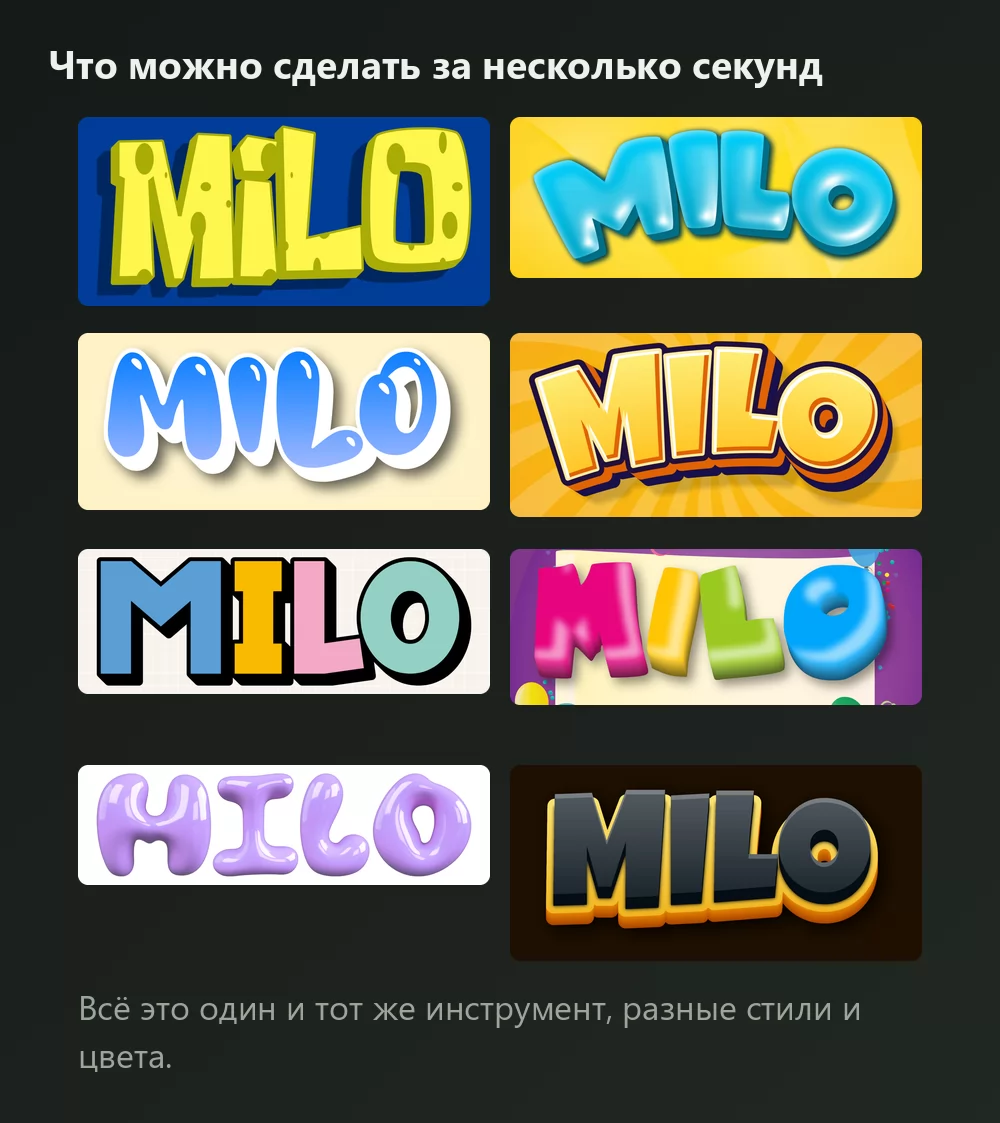
Всё это один и тот же генератор шрифта «Губка Боб», просто с разными стилями из списка. Ничего не устанавливается, аккаунт не нужен.
Как сделать текст в стиле «Губка Боб»
Шаг 1. Введите имя
Откройте генератор и замените образец текста на свой: имя, праздник, канал, заголовок. Буквы перерисовываются по мере ввода.
Шаг 2. Выберите стиль
Стиль сериала это жёлтая губчатая текстура с дырками и толстой тёмной обводкой. Именно его все и представляют, и он самый громкий из набора. Во вкладке «Стили» заливка, обводка и тень меняются по отдельности: форма остаётся, громкость убавляется.
Шаг 3. Выберите формат
Задайте формат до экспорта, и потом ничего не обрежется. 16:9 для превью видео, квадрат для аватара, широкая полоса для праздничной растяжки.
Шаг 4. Скачайте
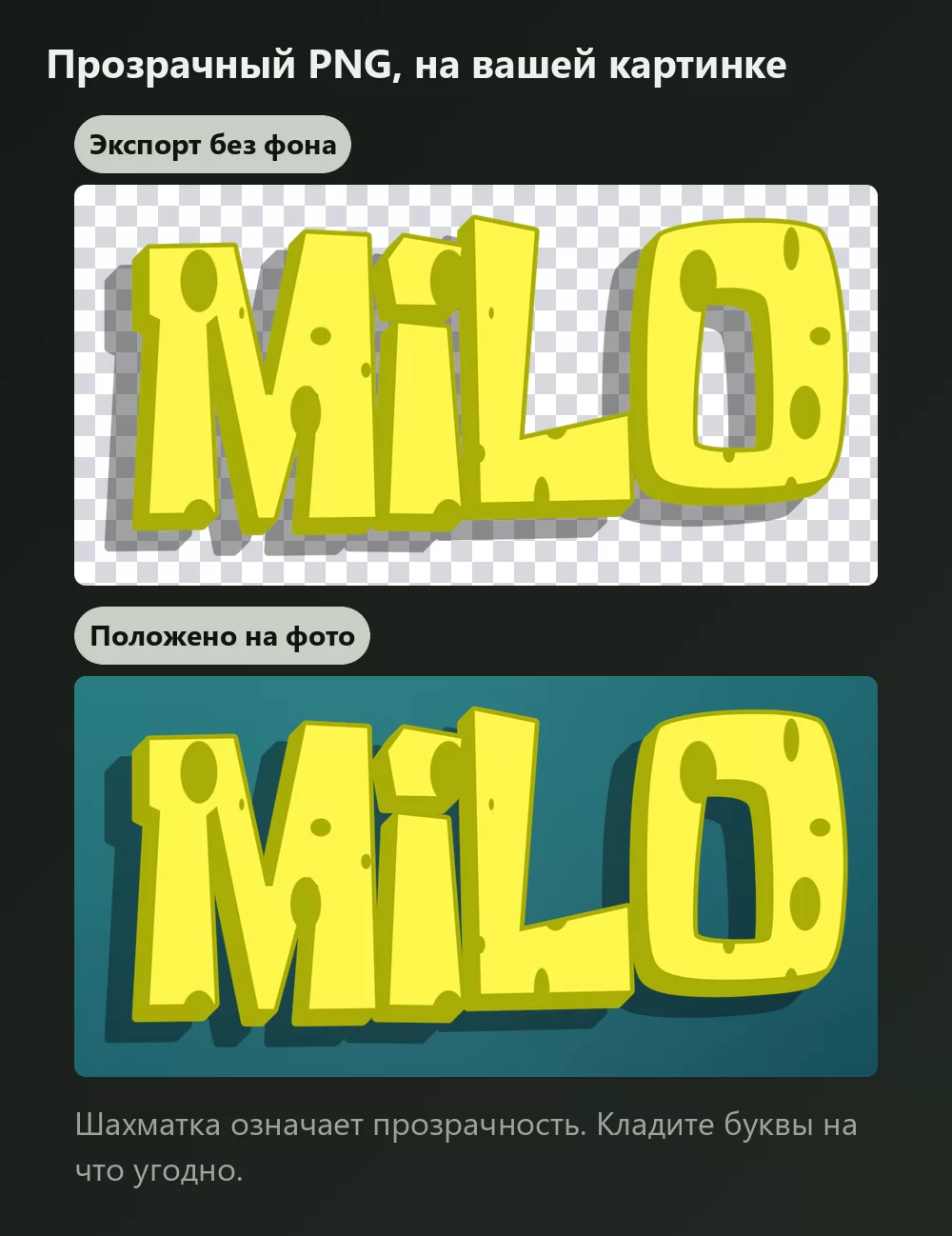
Во вкладке «Скачать» берите прозрачный PNG, если собираетесь класть буквы на своё фото, скриншот или приглашение. Именно эту опцию чаще всего пропускают, и именно она делает результат сделанным, а не приклеенным.
Длинные имена быстро занимают всю ширину
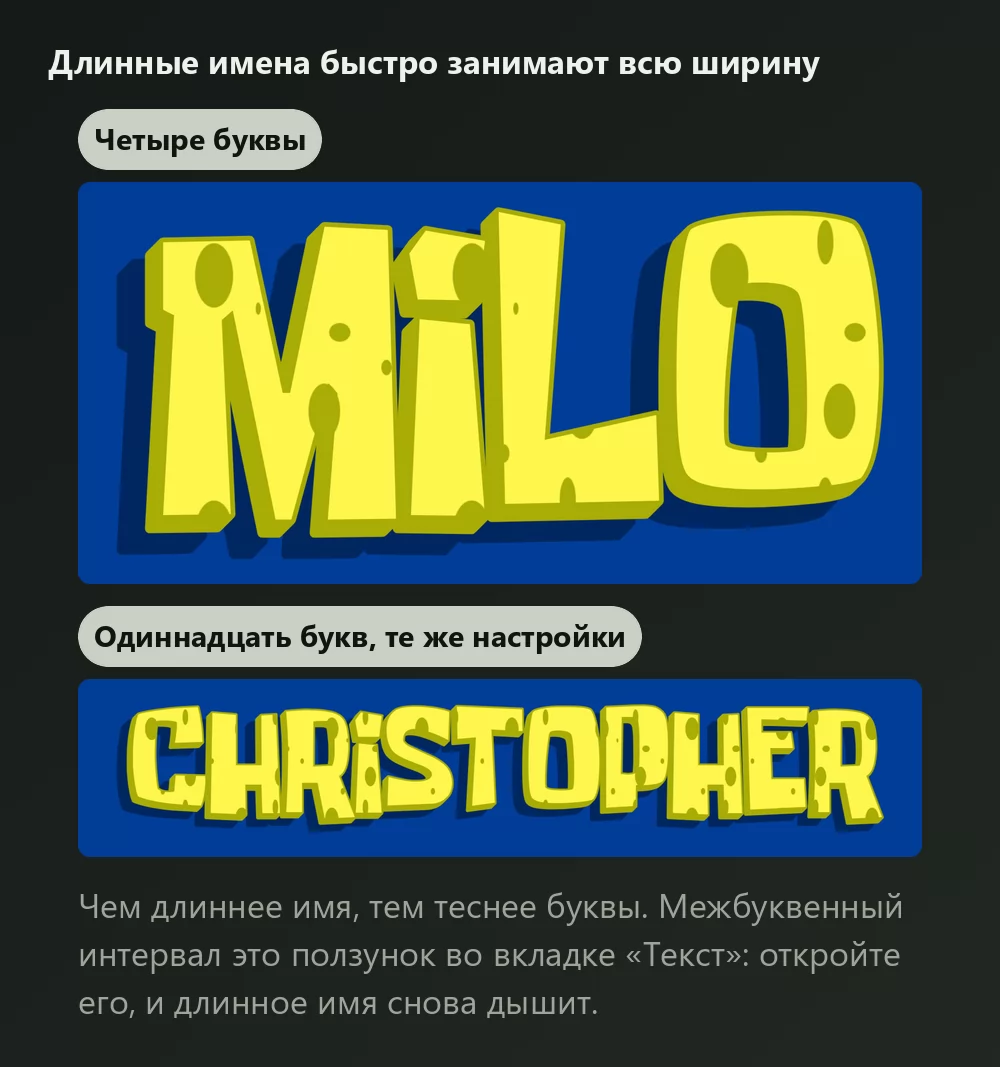
Чем больше букв, тем теснее они стоят. Межбуквенный интервал это ползунок во вкладке «Текст»: откройте его немного, и длинное имя перестанет выглядеть стиснутым. В той же вкладке лежат масштаб, межстрочный интервал, изгиб и поворот.
Два стиля, две задачи
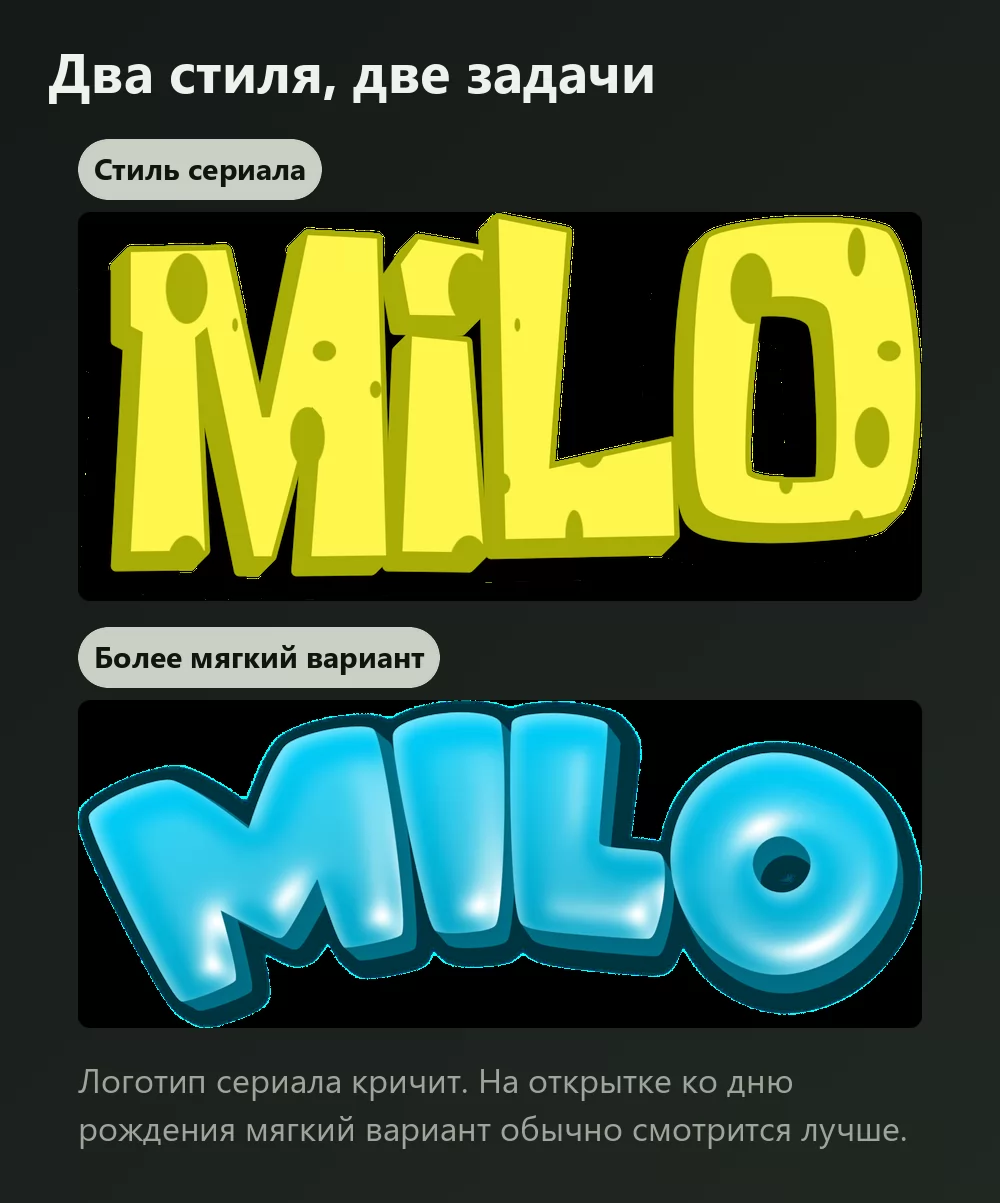
Решить стоит до начала, потому что задачи у них разные.
Стиль сериала уместен на превью, на афише, на всём, что должно бороться за внимание.
Более мягкий пузырьковый вариант обычно лучше смотрится на открытке ко дню рождения или на приглашении, где логотип сериала рядом с остальным начинает кричать. Та же идея, меньше громкости.
Какой шрифт, если хотите поставить его себе
Логотип на самом деле собран из двух шрифтов, и поэтому ни одна загрузка ему не соответствует.
«SpongeBob» это заказная надпись, нарисованная для сериала его создателем Стивеном Хилленбергом, внутри известная как Spongeboy TT1. Она никогда не выпускалась, так что всё бесплатное это фанатские копии.
«SquarePants» это настоящий покупной шрифт: Las Vegas Jackpot Кена Барбера для House Industries, где диагональ прописной Q заменена плоской перекладиной.
У самой скачиваемой копии есть предупреждение от того, кто её сделал. Krabby Patty за авторством Seil перевалила на DaFont за 708 000 загрузок. Её автор объясняет, что глифы автоматически обведены по низкоразрешённым игровым текстурам, прямо говорит, что она плохо масштабируется, и указывает на Spongeboy Me Bob или Some Time Later. Для мелкого текста она годится. В размере заголовка обводка становится видна: края расплываются и бугрятся ровно там, где буквы крупнее всего.
Это же и честная причина использовать генератор для заголовка. Шрифт даёт формы букв; губчатая текстура, дырки, обводка и тень это эффекты поверх.
Как сделать текст «Губка Боб» в Canva
Как сделать текст «Губка Боб» в Photoshop
Установите копию вроде Krabby Patty, наберите текст, затем соберите обработку стилями слоя:
- Обводка, снаружи, очень тёмным синим или чёрным, толстая.
- Наложение цвета в жёлтом, или лёгкий градиент для небольшого объёма.
- Тень, со смещением вниз и вправо, довольно плотная.
Дырки губки это то, чего шрифт не даст. В сериале они нарисованы внутри каждой буквы, так что воссоздать их значит нарисовать мягкие эллипсы на слое сверху, обрезанном по тексту.
Как сделать текст «Губка Боб» в Word
Установите шрифт, наберите текст и задайте обводку и тень через эффекты текста. Эффекты Word намного грубее, чем в графическом редакторе: для всего, что пойдёт в печать, экспортированный PNG будет выглядеть лучше того, что Word умеет собрать.
На телефоне
Установить шрифт и пользоваться им в большинстве приложений нельзя ни на iOS, ни на Android. Генератор работает в браузере телефона, поэтому практический путь такой: сделать PNG на телефоне, сохранить его в галерею и добавить в том приложении, которым вы пользовались.
Шрифт «Губка Боб» бесплатный?
Фанатские копии скачиваются бесплатно и обычно свободны для личного использования: приглашение на праздник, школьный проект, имя на своих обоях. Условия отличаются, поэтому перед любой оплачиваемой работой читайте файл, идущий с загрузкой. Las Vegas Jackpot, половина «SquarePants», это обычный коммерческий шрифт, который лицензируют как любой другой.
Учтите также, что лицензия на шрифт ничего не говорит о самом «Губке Бобе», товарном знаке Nickelodeon и Paramount. Генератор снимает вопрос о файле шрифта, потому что вы скачиваете картинку, а не распространяете шрифт.
Как получить прозрачный фон? Выберите прозрачный PNG во вкладке «Скачать», затем положите буквы поверх своей картинки.
Можно ли получить дырки губки одним только шрифтом? Нет. Дырки часть иллюстрации, а не форм букв. Генератор наносит их за вас; в Photoshop их пришлось бы рисовать на обрезанном слое.